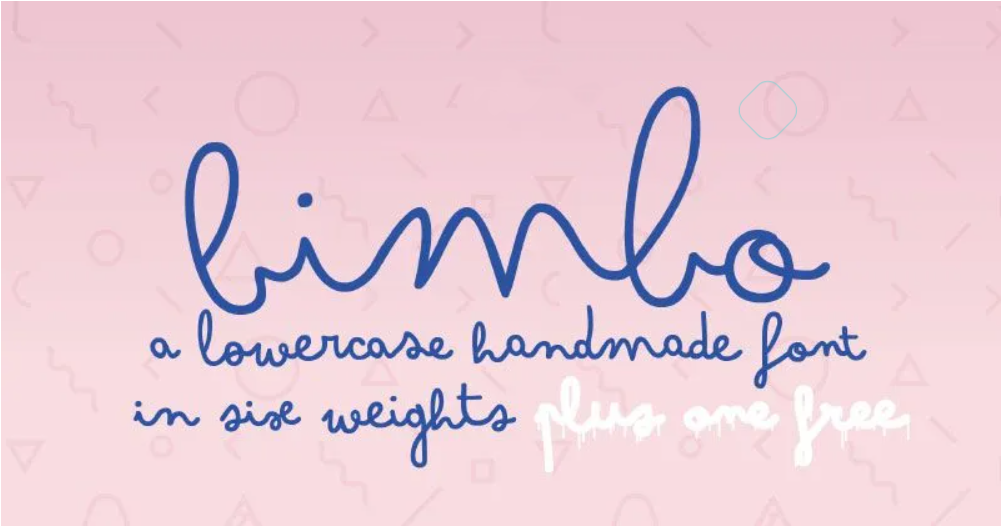
1. Giới thiệu về Font chữ Bimbo .
Bimbo là một họ phông chữ đơn dòng được Francesco Canovaro tạo ra vào năm 2018 cho Zetafonts như một phần mở rộng và thiết kế lại của phông chữ Arsenale White gốc được tạo ra với họa sĩ minh họa người Ý Jonathan Calugi.
Bimbo mở rộng thiết kế gốc với sáu độ đậm mới và hơn 300 ký tự mới để bao gồm hơn 70 ngôn ngữ sử dụng bảng chữ cái Latin, Hy Lạp và Cyrillic, đồng thời vẫn giữ được tính thẩm mỹ thủ công đã làm nên thành công của phông chữ gốc.
Bimbo về cơ bản là một phông chữ hiển thị, được sinh ra để tối giản chữ cái và logo, với khả năng cảm thụ chữ viết tay được tăng cường nhờ tính năng hoán đổi chữ cái mở tích hợp đảm bảo các chữ cái đôi luôn khác nhau.
Phông chữ mở và thiết kế đơn dòng cho phép dễ đọc ở kích thước nhỏ, khiến Bimbo trở thành phông chữ lý tưởng để tạo ghi chú viết tay giả và trò đùa siêu văn bản.